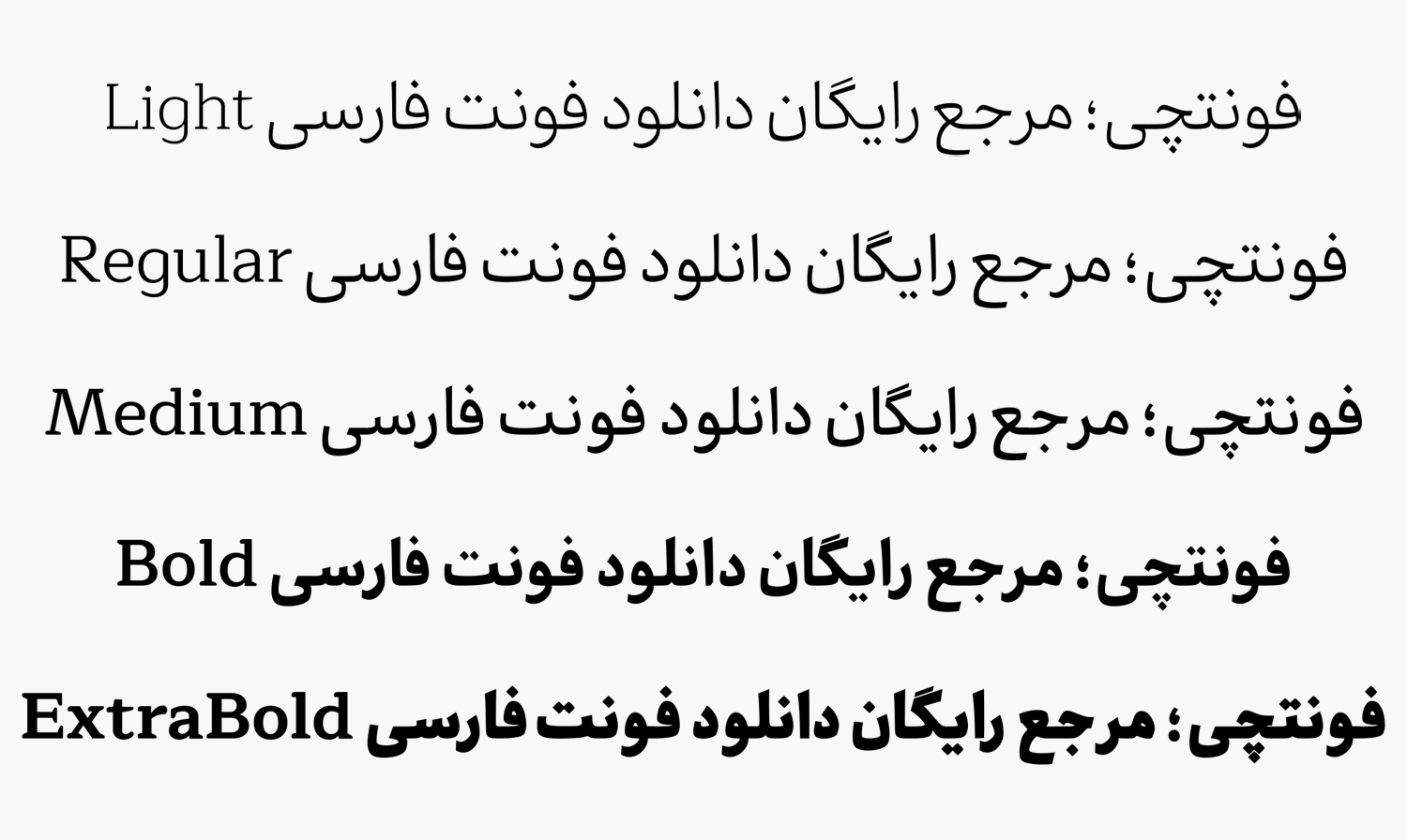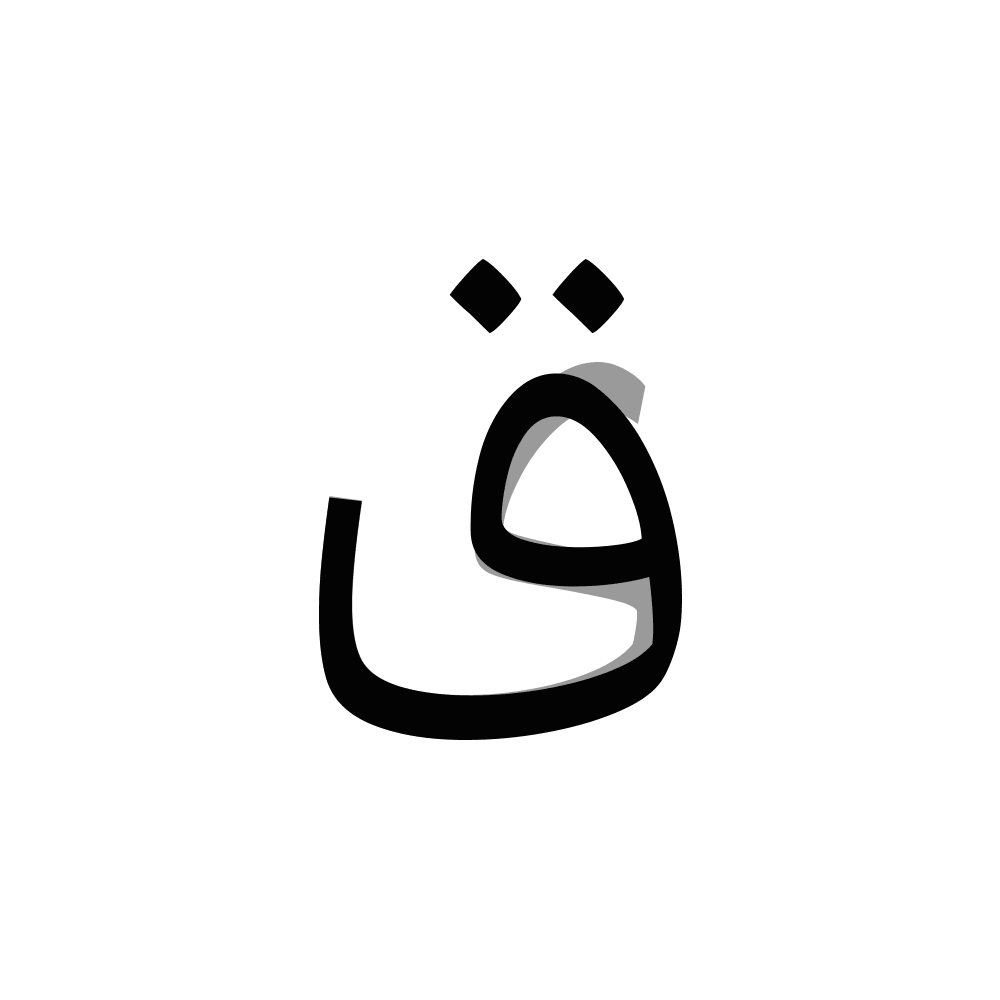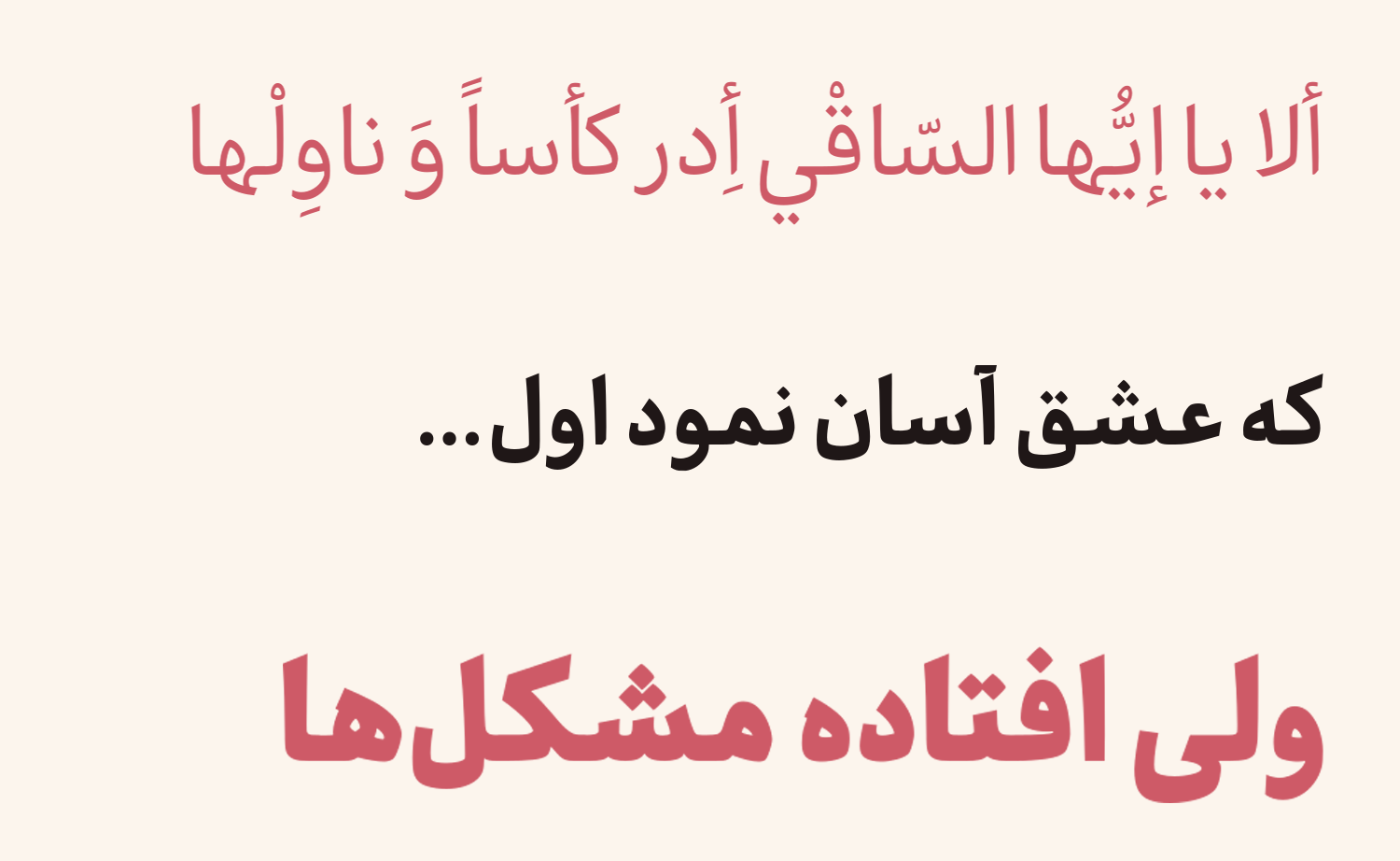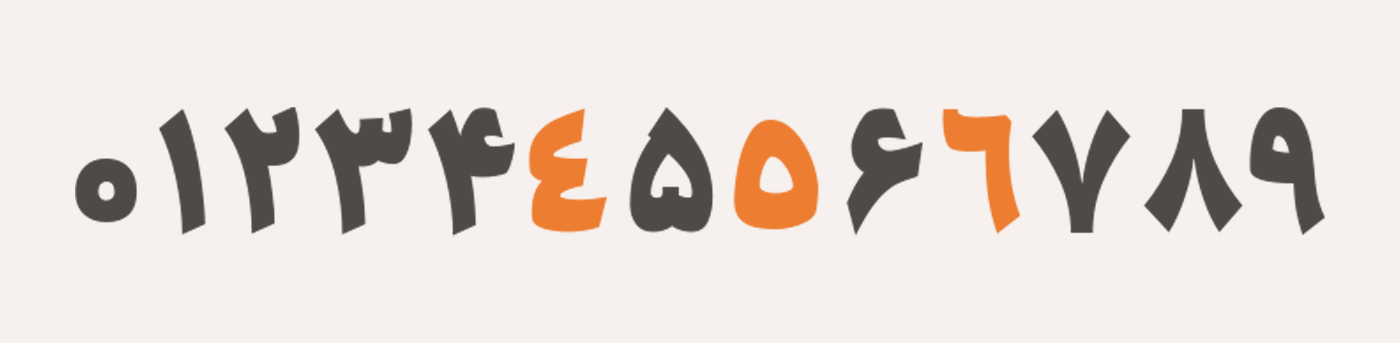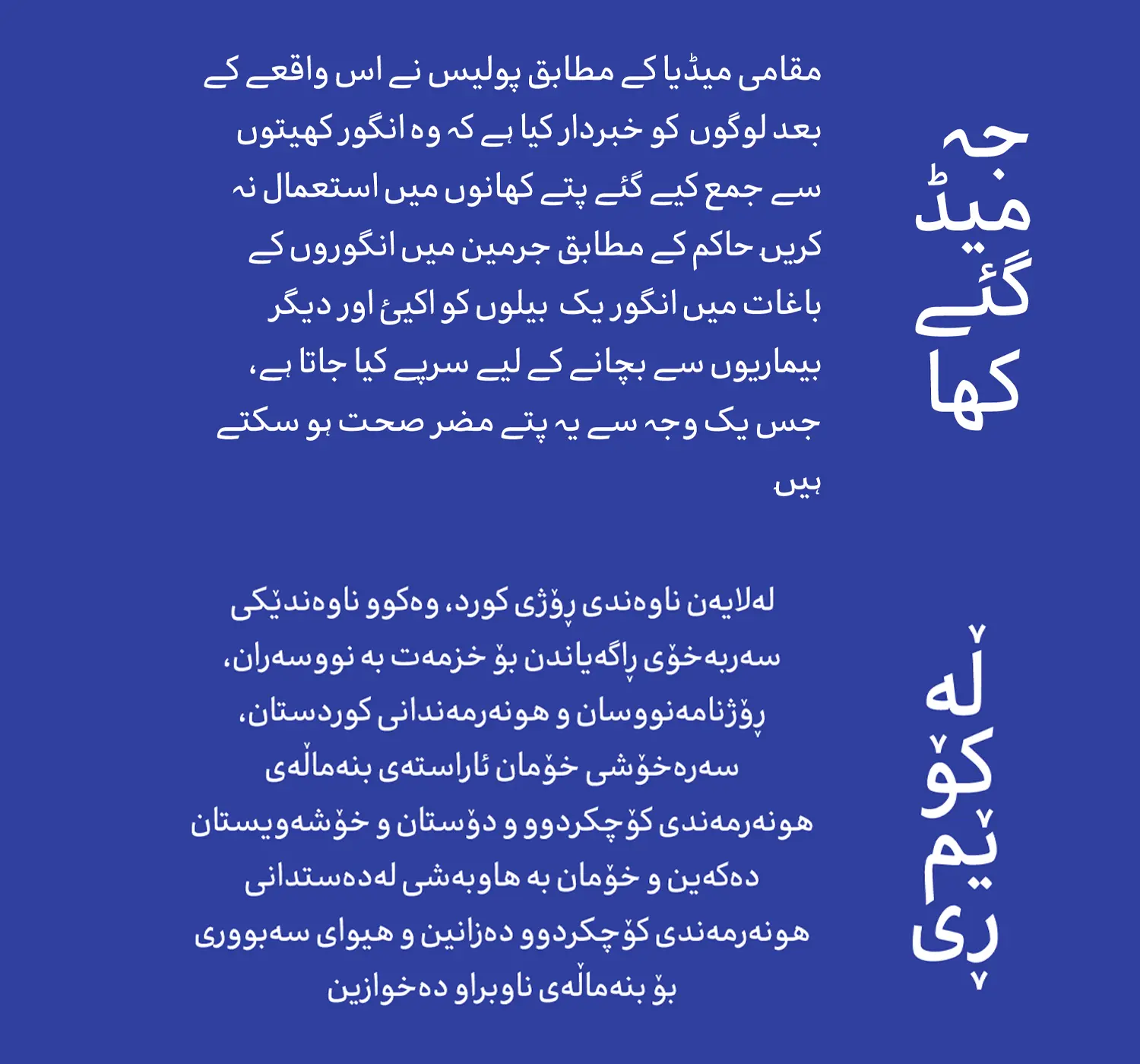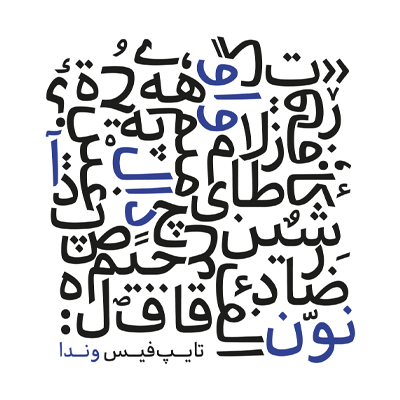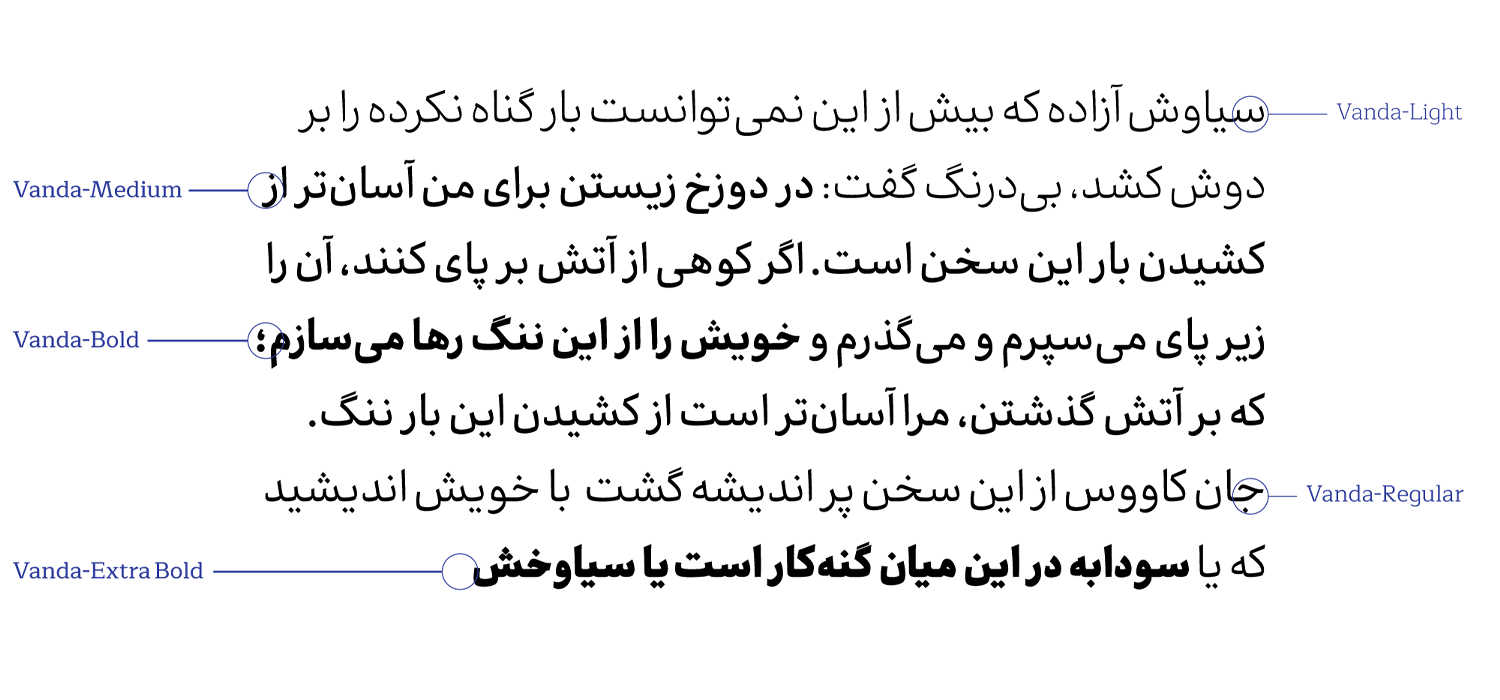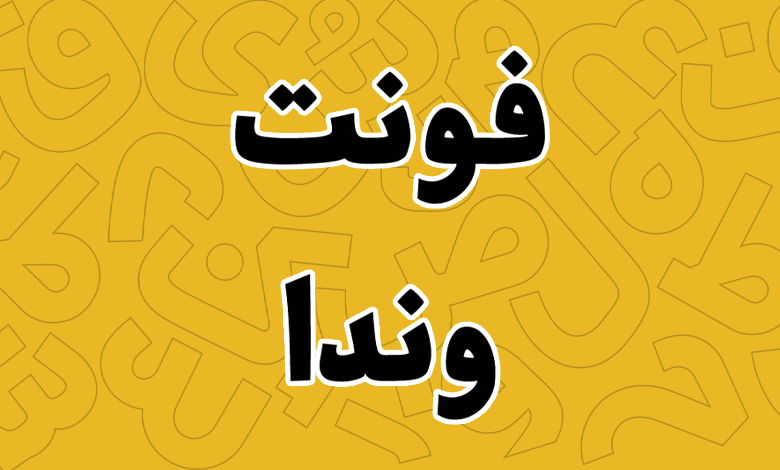
فونت وندا (Vanda)
| طراح | فائزه طاهری |
فونت وندا (به انگلیسی: Vanda) قلمی در گروه فونت مناسب متن است که با توجه به پشتیبانی از ۵ وزن مختلف، میتوان از آن برای متن کوتاه استفادهای برای فونت عنوان داشت یا اینکه در متنهای بلند از آن استفاده کرد. با توجه به ساختار و سبک طراحی این قلم، بیشترین کاربرد و کارایی را میتواند در صنعت چاپ و مطبوعات داشته باشد یا اینکه به عنوان وب فونت مورد استفاده قرار گیرد.
فائزه طاهری این قلم را در سبک نسخ طراحی کرده است و وندا نامی کاملا فارسی به معنی «دختری ایرانی به رنگ لاجورد» است. اسکلت و بدنه اصلی این قلم از فونت میترا الهام گرفته شده است که در آن توجه به تطابق و شباهت فرمها، به عنوان یکی از شاخصهای دیزاین در نظر گرفته شده است. امیر مصباحی نیز توسعه این قلم را در قالب فونت نرمافزاری به سرانجام رسانیده است.
در ادامه این نوشته از سایت فونتچی به نقد و بررسی کامل فونت وندا خواهیم پرداخت؛ قلمی که میتوانید از آن در صنعت چاپ بهعنوان فونت کتاب یا فونت روی جلد استفاده کرده یا اینکه در فضای وب از آن به عنوان فونت سایت، فونت عنوان و تبلیغات با جنبه نمایشی در وزنهای سنگین استفاده کنید.
این قلم بهدور از شخصیت صمیمی بوده و ضمن داشتن لحنی آرام، مودبانه و رسمی؛ در مقابل کاملا قانونمند بوده و به دور از آلایشهای فانتزی و تغییرات ناگهانی است.
اما این قانونمندی بههیچ وجه باعث نشده که جوانی و پویایی خود را از دست بدهد. ولی در عین حال اصالت خود را حفظ کرده و دارای ساختاری کاملا مدرن و امروزی است.
سبک طراحی و وزن فونت وندا
تغییر ضخامت با کنتراست کمتر در خط بدنه این فونت اصلیترین وجه تمایز این قلم با فونت میترا است؛ از همینجهت چون در گروه تایپ فیسهای کاملا هندسی یا کاملا خوشنویسانه قرار نمیگیرد؛ دارای فرم امروزی، لحن مدرن و ساختاری معاصر است.
فضاهای منفی محصور در مقایسه با فضاهای مثبت و منفی غیر محصور موکدتر و هویداتر هستند. این انتخاب برای افزایش قدرت خوانش (Readability) و میزان تفکیک و تشخص بصری کاراکترها (Legibility) در سایزهای کوچکتر صورت گرفته است.
ارتفاع کاراکترها متعادل است. محدوده پایین خط کرسی (Descender) کوتاه و کاسهها کمعمق هستند. حضور فرمها در فضای بالای خط کرسی (Ascender) پررنگ است، این تمرکز در خوانش متنهای طولانی نقش مهمی دارد.
پشتیبانی از ۵ زبان متنوع
فونت فارسی وندا از ۵ زبان مختلف خاورمیانهای و لاتین پشتیبانی میکند. اما قبل از اینکه به بررسی همه زبانها بپردازیم، باید گفت که این قلم برای نسخه انگلیسی دارای طراحی اختصاصی نبوده و از فونت رایگان و اپنسورس Maitree که چه به لحاظ فرمی و چه از نظر طراحی ظاهری نزدیک به آن دارد وام گرفته شده است. اما در خصوص زبانهای خاورمیانهای شرایط فرق میکند.
در نسخه عربی فونت وندا که برگرفته از همان حروف فارسی است هماهنگی را در تمامی حروف مشاهده میکنیم. تفاوتی هم ندارد که صفحه کلید شما روی زبان فارسی باشد یا عربی؛ در هر حالت هر دو زبان ساختار یکسانی دارند.
در این بین حروفی مثل «ك، ي، ة، ؤ، ئ» که دارای ظاهری متفاوت هستند کار شده تا بر اساس زبان صفحه کلید گلیفهای مختص آنها نیز تایپ گردد.
اعراب نیز در این قلم دارای ساختار استاندارد هستند. قرارگیری اعرابی نظیر تشدید یا همزه در جوار سایر اعراب اصلی به شکل هماهنگ و همنشینی روی هم قرار گرفته که ساختار منظمی را به فونت داده است.
از نظر پشتیبانی اعداد نیز ساختار برای هر دو زبان استاندارد است. افزون بر این اعداد هک شده فارسی برای زبان عربی و انگلیسی نیز در پوشه مخصوص با پیشوند FD که مخفف Farsi Digits است نامگذاری شده و قابل استفاده هستند. این گروه از فایل فونت بدینصورت است که حتی وقتی صفحه کلید روی زبان انگلیسی یا عربی قرار داشته باشد یا اینکه از صفحه کلید ماشین حساب استفاده کنید، باز هم اعداد فارسی تایپ خواهد شد.
سایر زبانهایی که این قلم از آنها پشتیبانی میکند عبارتند از کردی، اردو و پشتو که همه این زبانها نیز تکیه بر رسم خط فارسی دارند؛ اما مشابه نمونه عربی، برخی ساختارهای متفاوت را نیز با خود به همراه دارند.
به عنوان نمونه حروفی مانند «ﮧ، ﮩ، ے» در زبان اردو متفاوت از زبان فارسی هستند که گاها در زبان پشتو نیز مورد استفاده قرار میگیرند و در این قلم روی آنها کار شده است.
دارای گلیف های تزئینی و نمایشی
ویژگی دیگر وندا پشتیبانی از گلیفهای تزئینی مطابق با زبانهای خاورمیانهای؛ خصوصا در زبانهای شرقی اردو است. در سه زبان کردی، پشتو و اردو به وفور میبینیم که از طرههای تزئینی و برخی کاراکترها که به شکل «۷، ط، ء» هستد بر روی کلمات یا در برخی حروف در کرسی پایین استفاده میشود.
در نمونه تصاویری که در بخش زبان برای این زبانها مشاهده کردید همین ساختارها وجود دارد. فونت وندا این گلیفهای تزئینی و نمایشی را با خود به همراه دارد تا برای کارهای گرافیکی که جنبه فرهنگی و هنری یا تبلیغاتی دارند استفاده خلاقانه داشته باشید.
در تمامی وزنهای نازک تا ضخیم فونت وندا، حروفچینی طوری صورت گرفته تا آن ظاهر رسمی در دندانهها، منحنیها، خطوط قائم و سایر بخشهای تمامی حروف به شکل هماهنگی صرفا با افزایش حجم و در عین حال کاسته شدن از کنتراست قلم صورت گیرد.